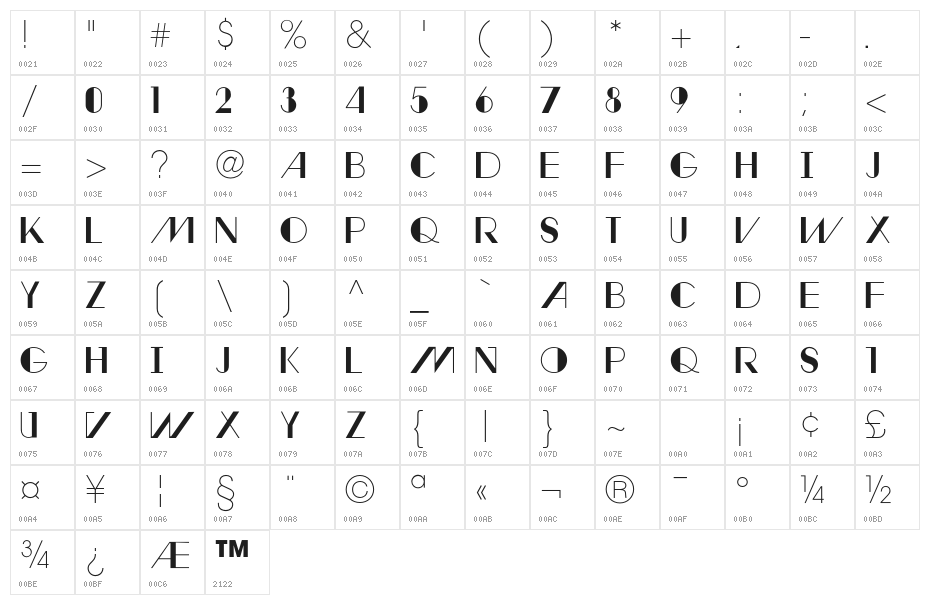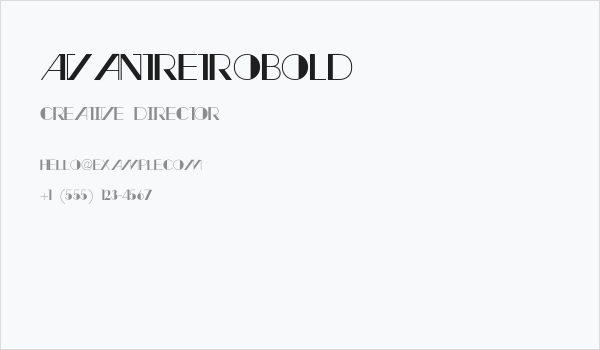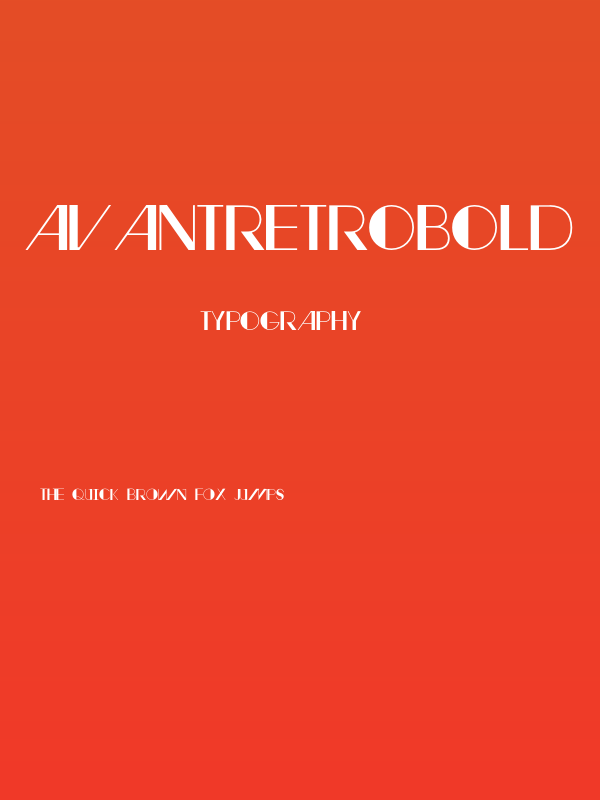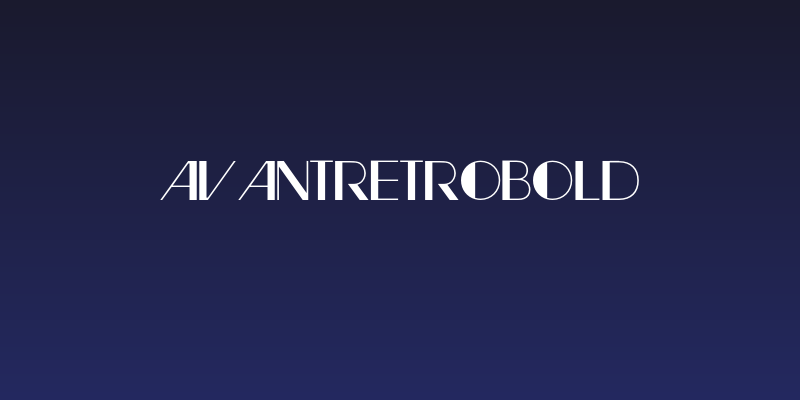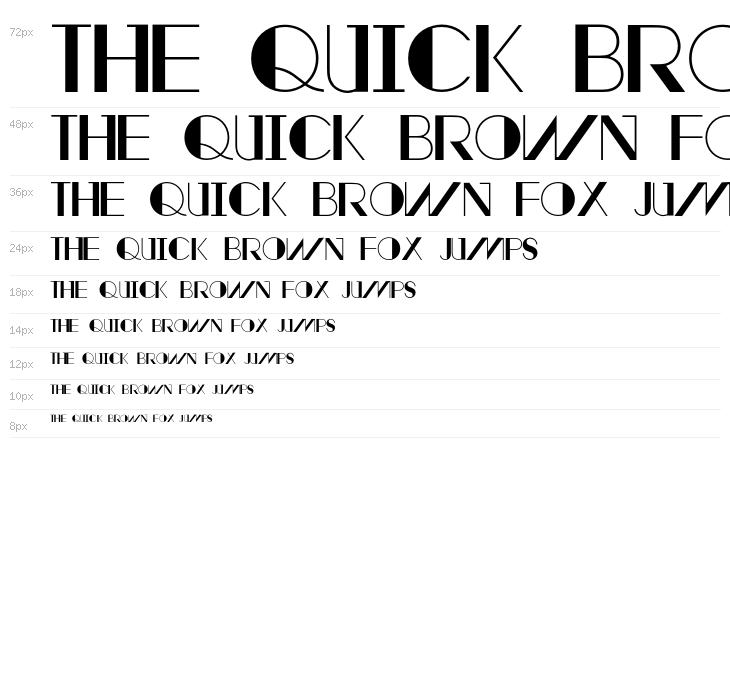
AvantRetroBold Font
✎ Thick
इस फ़ॉन्ट में शामिल हैं 131 अक्षर। विवरण देखने के लिए किसी भी अक्षर पर क्लिक करें।
| श्रेणियाँ | Thick |
| कंट्रास्ट | High |
| उपयोग का मामला | Headlines, Logos, Posters |
| सुझाए गए प्रोजेक्ट | Ideal for modern branding, advertising campaigns, poster designs, and editorial headlines. |